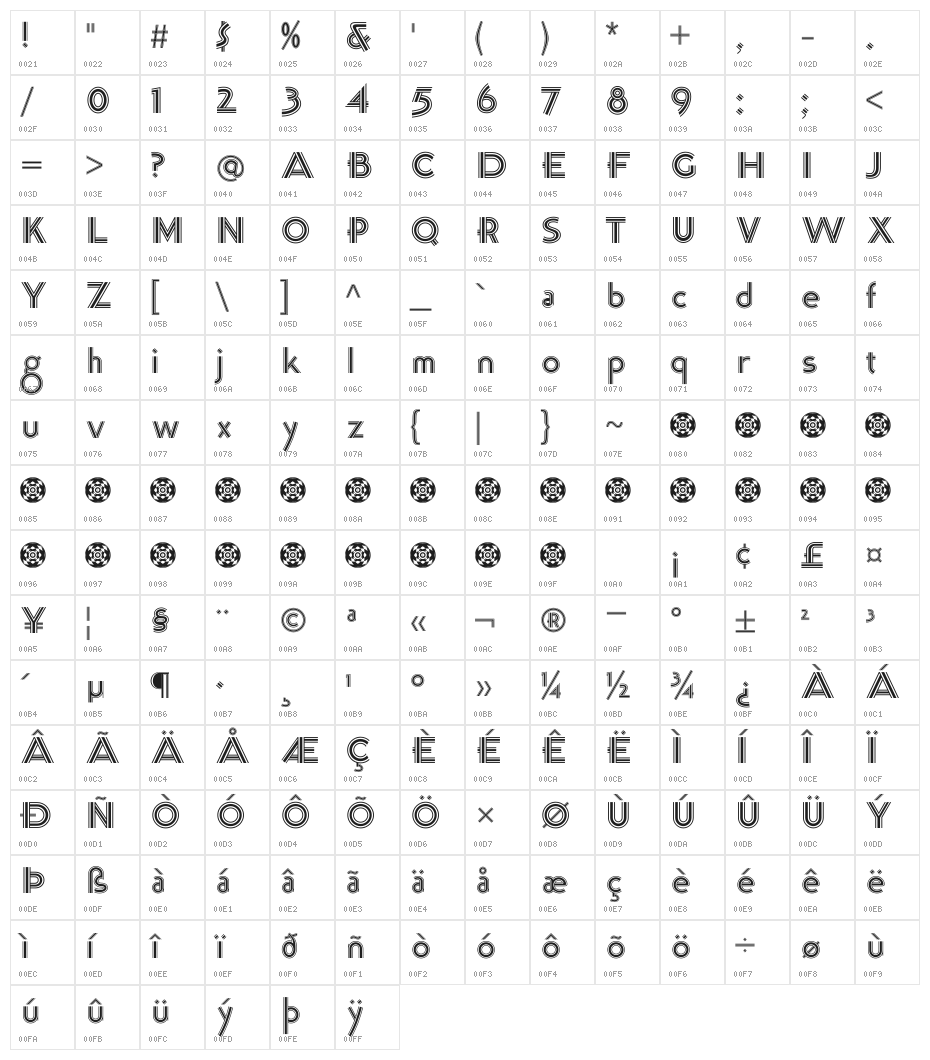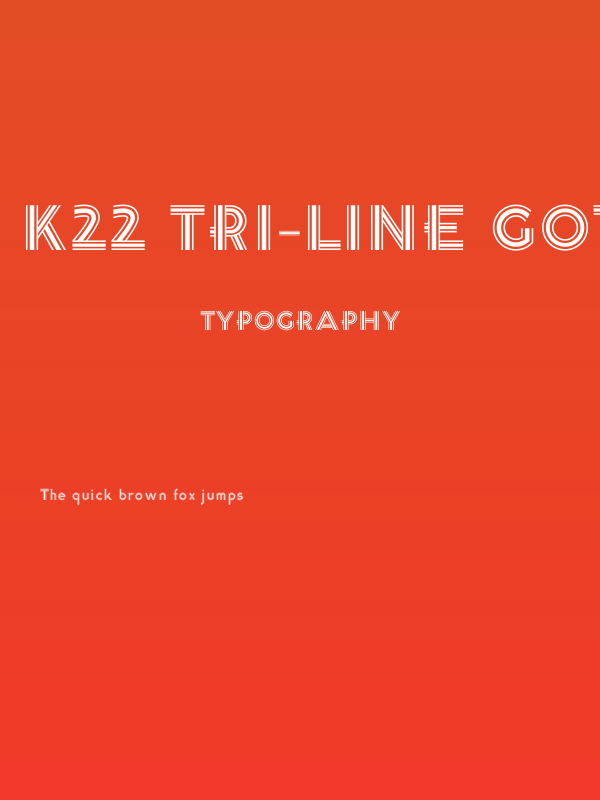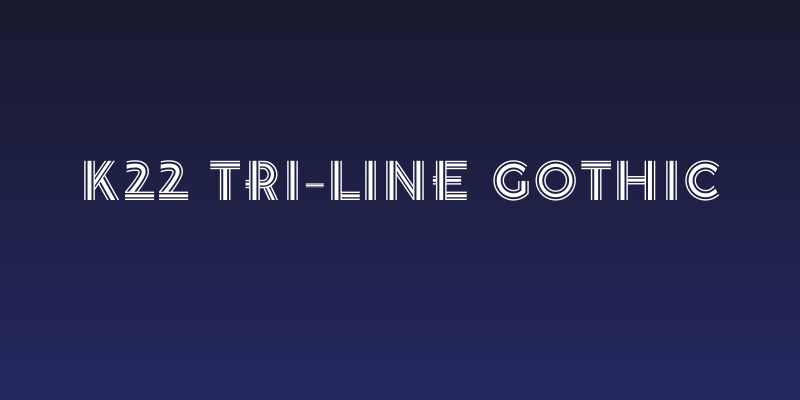
K22 Tri-Line Gothic Font
| उपयोग का मामला | Headlines, Logos, Posters |
| सुझाए गए प्रोजेक्ट | Ideal for branding, posters, and headlines where a bold and modern aesthetic is desired. |